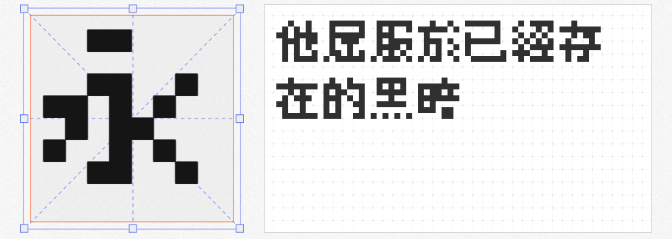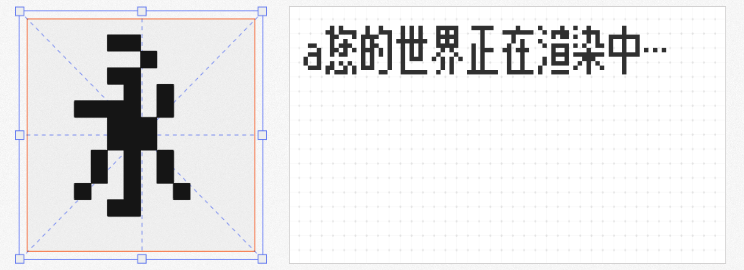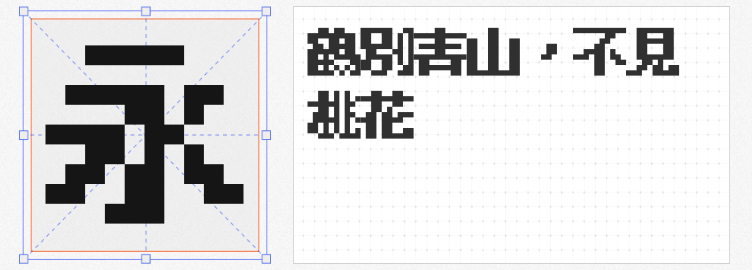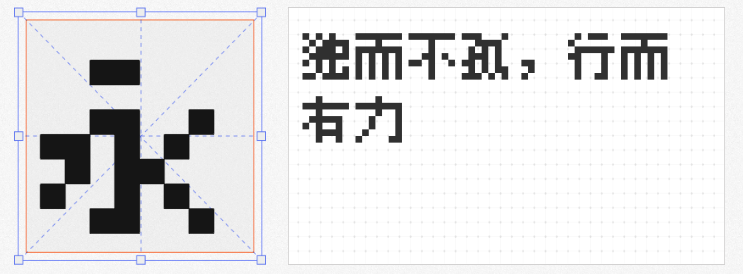
在像素艺术与复古游戏风格回潮的当下,像素字体凭借其独特的颗粒感与怀旧气质,成为游戏界面、数字海报、品牌视觉等领域的热门选择。本文精选四款免费可商用的优质像素字体,兼顾繁简中文支持与创意设计,助力设计师轻松打造高辨识度作品。
基于日本美咲フォント改良的精品点阵体7×7,针对繁体中文环境优化,修正了标点符号与日式习惯写法,并大幅扩充字符集。其7×7的超小像素格构建出棱角分明的字形,每个笔画均由精准的像素点组成,完美适配像素画、复古游戏UI等场景。无论是模拟老式电子屏,还是营造未来科技感,这款字体都能以极简风格传递强烈视觉冲击。
作为「方舟像素字体」的过渡方案,缝合怪像素字体 8px以“拼接”为核心理念,融合多款经典像素字体的特点,形成独特的中性风格。8px的紧凑尺寸适合高密度信息展示,字形结构平衡了可读性与装饰性,尤其适用于独立游戏、动态像素动画等需要快速吸引眼球的场景。其开源属性更鼓励设计师二次创作,探索像素字体的可能性边界。
原名k8x12j的目哉像素体 Orig,基于开源字体k8x12优化,以8×12的像素格还原中日文点阵精髓。字形保留了早期计算机字体的机械感,同时通过微调笔画比例提升现代审美下的易读性。无论是用于模拟CRT显示器效果,还是作为标题字体与现代无衬线体搭配,都能营造出跨越时空的对话感。
升级版精品点阵体9×9 1.9 B在延续点阵风格的基础上,融入M+ BITMAP FONTS与ベストテン的基因,新增简体中文、颜文字符号及直排特性,支持OpenType高级排版功能。9×9的像素格赋予字形更多细节表现空间,适合需要兼顾复古情怀与复杂排版的项目,如像素风书籍装帧、多语言游戏界面等。